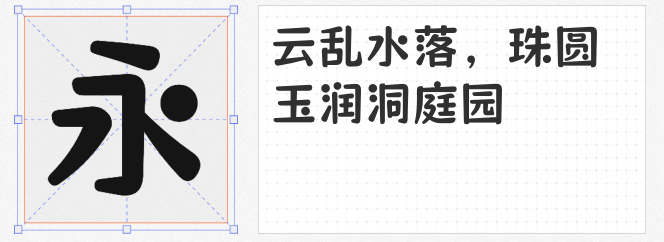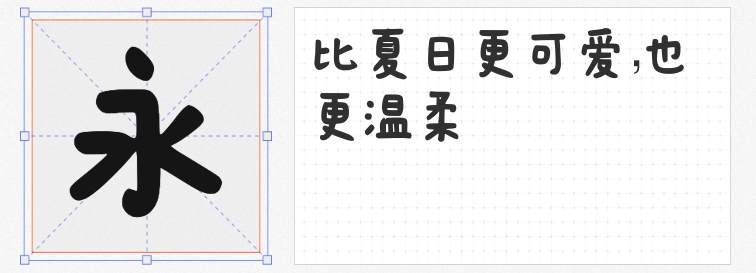
在儿童品牌、文创产品或社交媒体创意设计中,圆润可爱的字体总能瞬间软化视觉语言,传递温暖治愈的氛围。本文精选四款风格各异的免费商用字体,兼顾灵动性与实用性,助设计师轻松打造萌系视觉作品。
1. 也字工厂小石头体
这款字体以“软萌”为核心设计语言,通过夸张的粗细对比与圆润转角,营造出类似果冻般的Q弹质感。笔画书写自由洒脱,部分收笔处保留毛笔飞白效果,既保留手写温度又增添率真个性。在儿童零食包装或幼儿园活动海报中,其活泼的视觉张力能快速吸引目光,而标题与短文案的排版中,强烈的笔画对比更能强化记忆点。
2. 字体家AI造字春风
由AI生成的这款字体突破传统手写框架,通过算法优化实现笔画间的自然过渡。圆润的弧线中暗藏动态韵律,仿佛每个字都在随风轻摆,尤其适合春季主题或环保类设计项目。其卡通感造型在社交媒体表情包、线上活动banner等场景中表现突出,既能保持信息可读性,又赋予画面轻盈的呼吸感。
3. 平方萌萌哒
横画微弯的独特设计让这款字体自带“歪头杀”萌感,适度简化的结构避免了过度圆润带来的模糊感。在文具品牌LOGO或手账素材设计中,其恰到好处的俏皮度既能吸引年轻女性群体,又不会显得过于低龄化。搭配手绘插画时,字体的手写特质能与图形元素自然融合。
4. 猫啃珠圆体
基于标小智龙珠体改造的这款字体,将棱角全部转化为饱满的珍珠圆弧,在保持辨识度的同时注入天真气质。在母婴产品详情页或儿童绘本标题中,其无拘无束的视觉风格完美契合“自由成长”的核心理念。作为正文字体使用时,均匀的笔画粗细确保了长文本的阅读舒适度,堪称实用性与萌感兼具的典范。